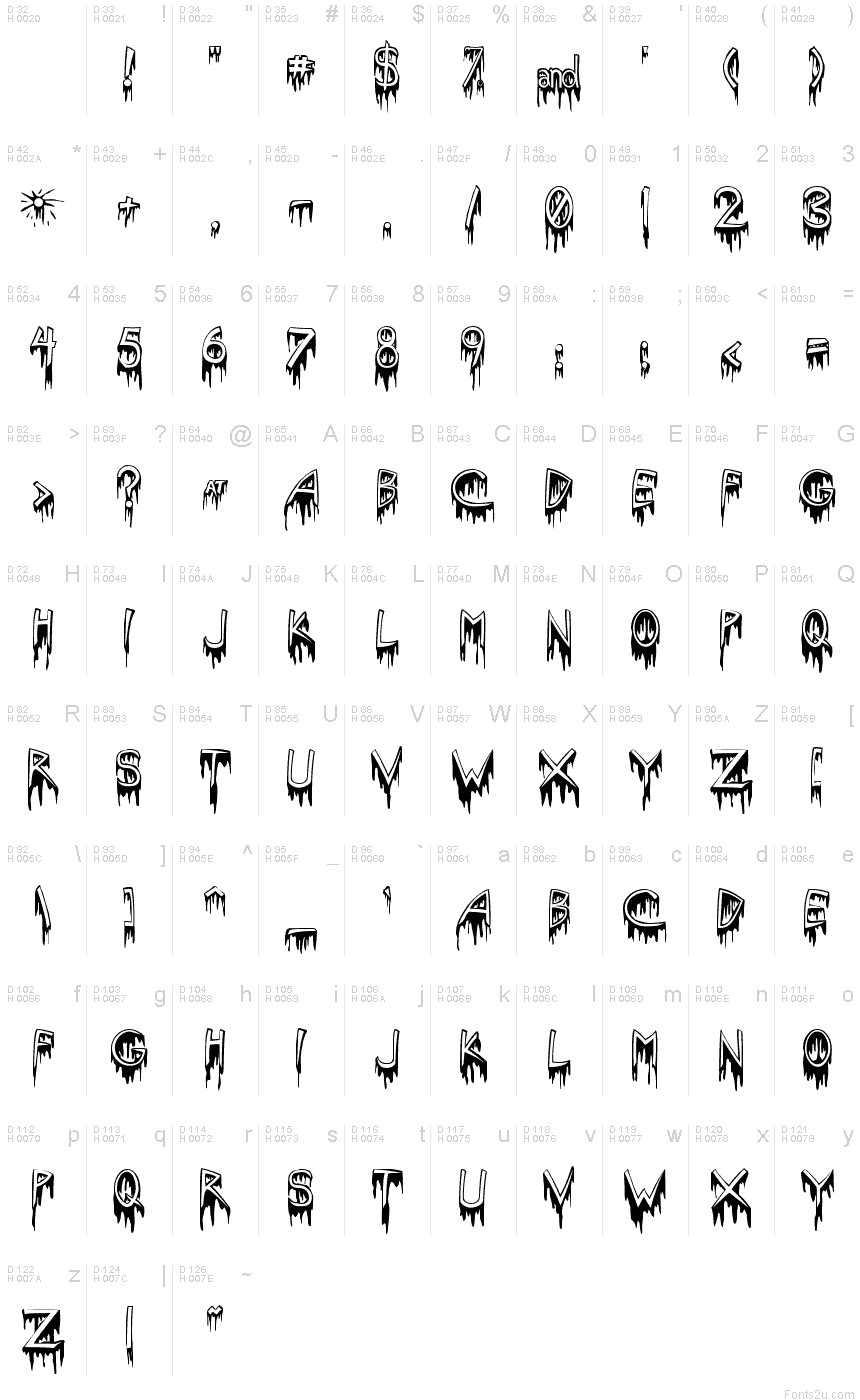
يُعد خط Solstice of Suffering، الذي صممه Leon del Muerte، خط عرض مجاني بطابع الرعب، يحمل صدمة الأفلام القديمة لوحوش السينما. تبدو الحروف الكبيرة منتفخة وثقيلة، مع بروزات لزجة وتقطرات داخلية خشنة تجعل الحروف تبدو وكأنها تذوب على السطر.
يناسب هذا الخط ملصقات الأفلام، ومنشورات الهالوين، وتصاميم أغلفة موسيقى البانك والميتال، ورسومات بيوت الرعب، وبطاقات العناوين القاتمة، حيث تحتاج إلى خط مجاني بظلال قوية و"لزجة". استخدمه للعناوين القصيرة، أو الشعارات، أو الحروف المزخرفة عندما تريد أن تنقل الحروف نفسها الحالة المزاجية، حيث أن نمط التقطر المتكرر يقوم بمعظم المهمة.